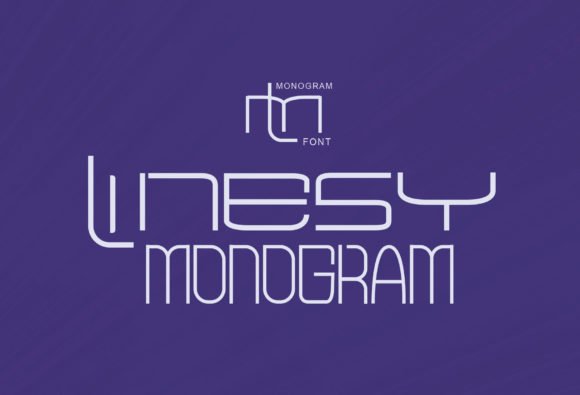
Creativefabrica Linesy Font 2021
[Creativefabrica] Linesy Font (2021)
Linesy - простой и аккуратный шрифт без засечек.
Его естественный и уникальный стиль делает его невероятно подходящим для большого количества дизайнов.